Introducción al diseño cristiano y la importancia de las fuentes tipográficas
El diseño gráfico en el contexto de las iglesias cristianas tiene una importancia considerable, ya que se encarga de transmitir mensajes, valores y conceptos fundamentales a través de elementos visuales. En este sentido, las fuentes tipográficas juegan un papel crucial en la comunicación visual, ya que pueden reflejar adecuadamente la identidad y los valores espirituales que se desean transmitir. Una tipografía bien elegida puede fortalecer y mejorar la recepción del mensaje, favoreciendo así una conexión más profunda entre el contenido y la audiencia.
Las fuentes tipográficas idóneas son aquellas que no solo se adaptan estéticamente al resto del diseño, sino que también encapsulan la esencia del mensaje evangélico. En este contexto, es vital contar con una variedad de fuentes que puedan mantener la coherencia entre el contenido escrito y la identidad visual de la comunidad religiosa. Las tipografías pueden aportar solemnidad, tranquilidad, alegría u otras emociones que son esenciales en la comunicación espiritual, y su uso adecuado refuerza el mensaje y promueve una mayor comprensión y conexión.
Este artículo tiene como objetivo principal proporcionar un listado de sitios web donde se pueden descargar fuentes tipográficas gratuitas, especialmente seleccionadas para el diseño cristiano. Estas fuentes ayudarán a los diseñadores y líderes de comunidades a elegir tipografías que resuenen con sus públicos, realzando así sus mensajes visuales. Al finalizar esta lectura, se espera que los lectores cuenten con nuevas herramientas útiles para enriquecer sus proyectos de diseño dentro del ámbito cristiano.
Criterios para seleccionar las mejores fuentes tipográficas
Al seleccionar fuentes tipográficas para proyectos de diseño cristiano, es crucial prestar atención a ciertos criterios que ayudarán a garantizar que la tipografía elegida cumpla con los objetivos del diseño. Uno de los aspectos más fundamentales es la legibilidad. Una fuente debe ser fácilmente legible, especialmente cuando se utiliza en textos largos, como artículos, boletines y materiales de estudio bíblico. Fuentes complicadas o demasiado estilizadas pueden dificultar la lectura y, por ende, el entendimiento del mensaje espiritual.
Otro criterio esencial es la estética. La tipografía debe tener un diseño atractivo que resuene con la audiencia y complementen el tono del proyecto. Por ejemplo, fuentes serenas y elegantes pueden ser más adecuadas para publicaciones religiosas formales, mientras que las fuentes más modernas y llamativas podrían funcionar bien en materiales orientados a una audiencia joven.
El tono que proyecta la fuente también juega un papel vital. Algunas fuentes pueden evocar sensaciones de reverencia y solemnidad, mientras que otras pueden parecer más informales. Es importante seleccionar una tipografía que se alinee con el mensaje que se desea transmitir y que, al mismo tiempo, respete la naturaleza y los valores del contexto cristiano.
Además, la tipografía puede complementar o mejorar el mensaje espiritual. Fuentes con un diseño inspirado en la iconografía cristiana o aquellas que imitan la escritura manuscrita pueden añadir una capa adicional de significado y profundidad a los textos religiosos, haciendo que el mensaje espiritual tenga un mayor impacto.
Finalmente, es crucial evaluar la calidad de la fuente gratuita. No todas las fuentes disponibles en línea cumplen con los estándares necesarios para un diseño profesional. Al analizar fuentes gratuitas, es recomendable verificar su origen, los comentarios de otros usuarios y, si es posible, probar la fuente en diferentes contextos para asegurarse de que mantiene su calidad en todas las aplicaciones y tamaños.
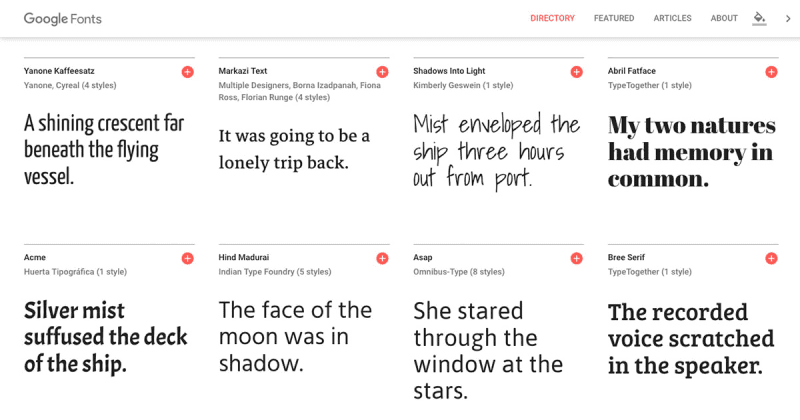
Listado de los 15 Mejores Sitios Web para Descargar Fuentes Tipográficas Gratuitas
1. Dafont – Dafont es ampliamente conocido por su vasta colección de fuentes gratuitas. Este sitio web ofrece una gran variedad de estilos, desde las más clásicas y solemnes hasta las más modernas y versátiles, lo cual lo hace ideal para proyectos de diseño cristiano.
2. Google Fonts – Google Fonts es una excelente opción para quienes buscan fuentes de alta calidad y libres de derechos. Su interfaz intuitiva facilita la búsqueda y previsualización de las fuentes antes de descargarlas.
3. Font Squirrel – Font Squirrel se especializa en ofrecer fuentes tipográficas que son 100% gratuitas para uso comercial. La selección es diversa y el sitio proporciona herramientas útiles como el generador de fuentes web.
4. 1001 Free Fonts – 1001 Free Fonts presenta una colección impresionante de fuentes gratuitas, organizadas en diferentes categorías temáticas, lo cual es particularmente útil para encontrar la tipografía adecuada para cada proyecto cristiano.
5. FontSpace – FontSpace ofrece una gran base de datos con más de 90,000 fuentes gratuitas. Sus categorías bien organizadas permiten encontrar fácilmente fuentes tipográficas que se alineen con temáticas religiosas y cristianas.
6. Behance – Behance no es solo una red de portafolios para diseñadores, sino también un excelente recurso para encontrar fuentes tipográficas gratuitas creadas por profesionales. Muchas de estas fuentes están disponibles para descargar y usar gratuitamente.